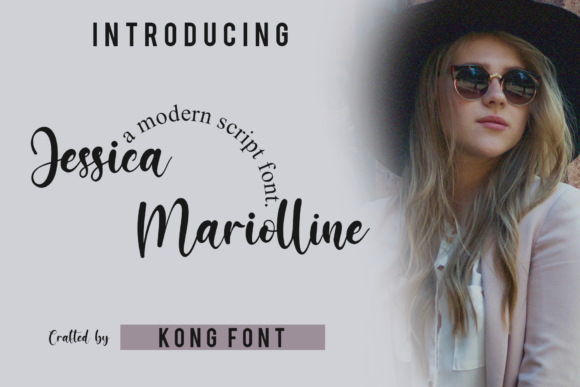
Jesicca Mariolline
Mencari elemen reka bentuk yang sesuai boleh menjadi mencabar, tetapi Jesicca Mariolline menawarkan koleksi luar biasa yang menaik taraf karya anda serta-merta.
Dicipta dengan ketepatan, Jesicca Mariolline menyediakan vektor yang bersih, tipografi yang licin dan lesen komersial untuk ketenangan fikiran.